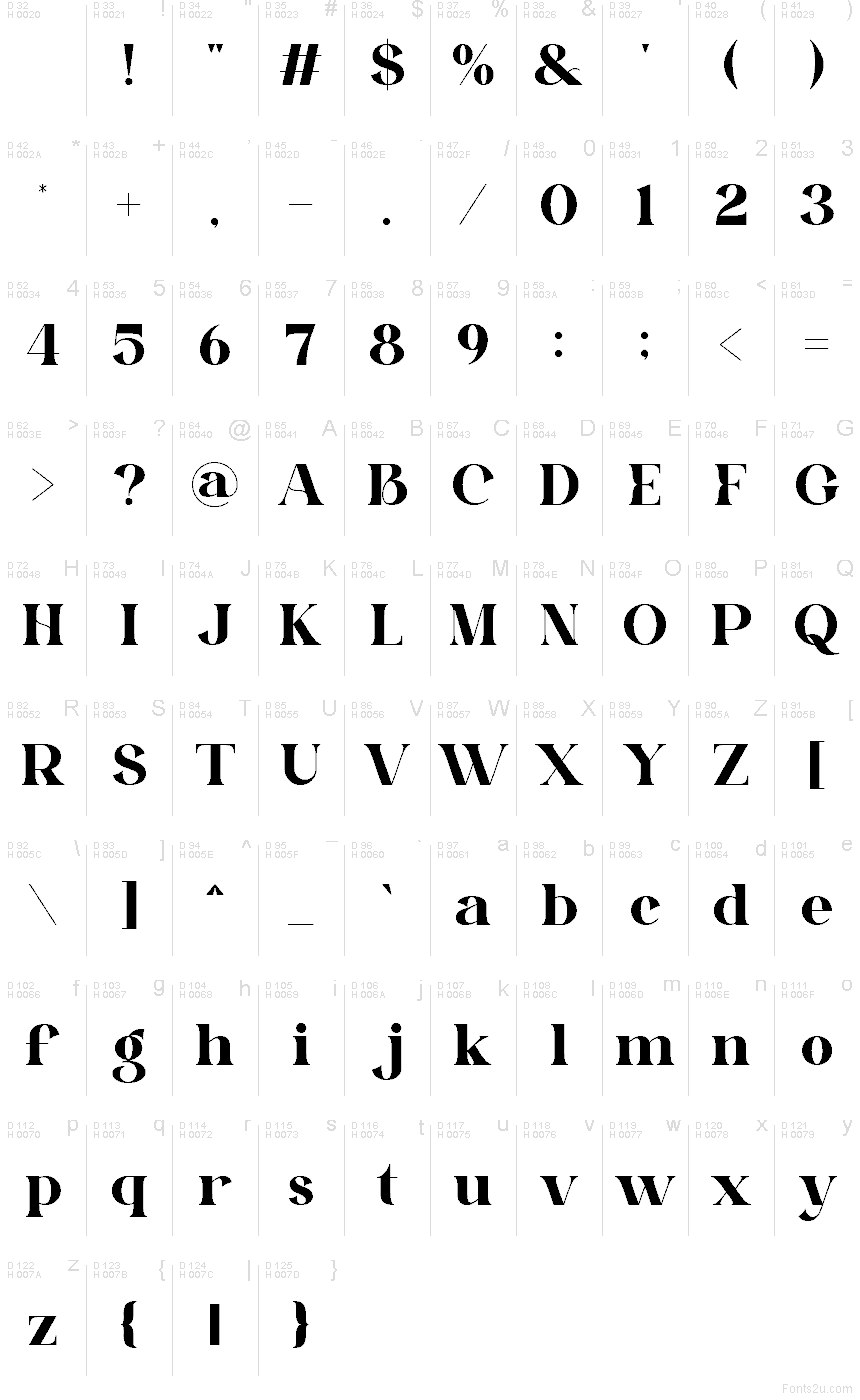
Biooris od Ermedia Studio je bezplatné dekorativní patkové písmo s extrémním kontrastem silných a tenkých tahů a vyrovnanou, módně laděnou siluetou. Jeho široké syté křivky se střetávají s vlasovými liniemi a jehlově ostrými patkami, což literám propůjčuje ukázněný, ale nepřehlédnutelně výstřední profil. Některé tvary se rozšiřují do nečekaných kapek, smyček a sevřených spojů.
Jeho nejvlastnějším polem působnosti jsou móda a luxus, zejména obaly parfémů, obálky časopisů a branding butiků, které dokážou zúročit toto spojení elegance a neotřelosti. U kulturních plakátů a přebalů hudebních alb mohou jeho sošné křivky souznít s vystřihovanými siluetami z papíru, ornamentální fotografií či strohými botanickými ilustracemi a proměnit text v součást samotného vizuálu, nikoli jen v neutrální popisek.